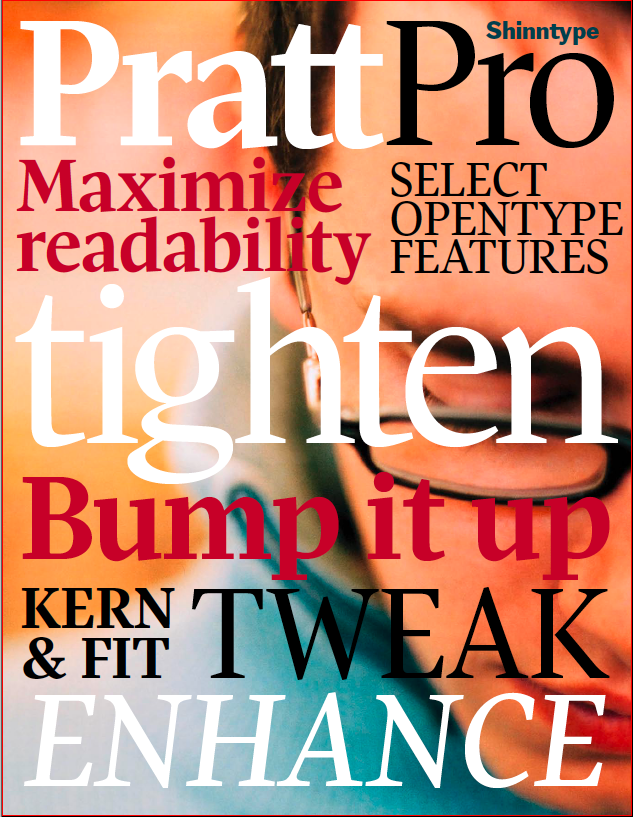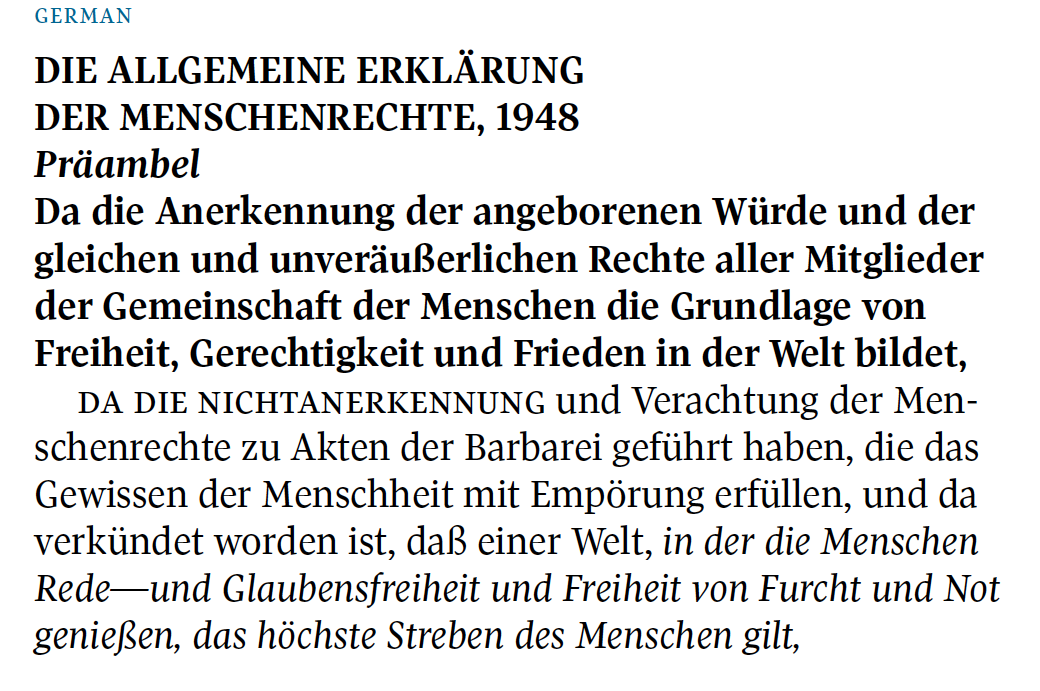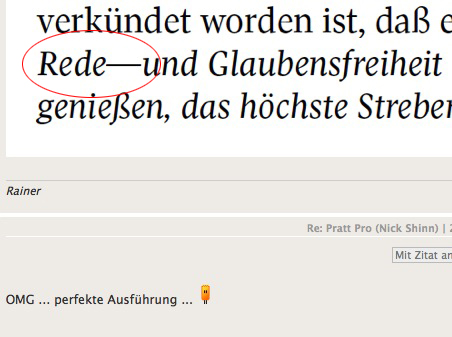
Pratt Pro (Nick Shinn)
Seit gestern ist Nick Shinns Pratt Pro der allgemeinen Öffentlichkeit zugänglich. Entwickelt für den Einsatz im kanadischen »Globe and Mail« ist sie seit 19. 1. 2009 auch als Kauf-Pro-Version erhältlich.
»With large x-height, semi-condensed proportions and short descenders, Pratt Pro is a hard-working old-style face that maintains readability in the most demanding of layouts. Despite its heft it is not without grace, displaying an economy of form, and enlivened by angled-slab detailing, thinning of ‘protected’ ?ne strokes, and a novel alternate lower case look.
When space is at a premium, Pratt Pro maximizes readability. Pica for pica, ?t the same amount of text into the same space, and Pratt Pro looks bigger than almost any other serifed text face – old style or modern – without awkward extender collisions in tight leading situations.This is clearly important for text sizes, but plays a role in multi-line headlines and decks too, where precise horizontal spacing and tight ?t call for a similar aesthetic in the vertical dimension.By the same token, when speci?ed in a layout with normal leading, a spacious effect is generated, and small size may be comfortably used for text without compromising legibility.Named after David Pratt, Design Director of The Globe and Mail, Canada’s national newspaper, who commis-sioned the face; it has been used for the paper’s body text since May 2007, setting hundreds of millions of words.
A precise, contemporary, economical face that maintains readability in the most demanding layouts.
Commissioned in 2007 for David Pratt’s radical redesign of Canada’s national newspaper, The Globe and Mail, it is available in text and headline styles, with a variety of OpenType features.«
atmet ein bisschen Weiß-Antiqua. Sehr schön!
OMG ... perfekte Ausführung ... :o
Ironie?
Das wage ich mal zu bezweifeln, dass es im Englischen üblich sei fremdsprachliche Texte falsch zu setzen :oops:
Ich fand halt die räumlich Nähe zwischen dem Satzfehler und dem "OMG … perfekte Ausführung …" so schön :cheer:
ich nehme mal an dass der geviertstrich ohne vor- und nachbreite gestaltet wurde ... wenn dann kein Raum davor und danach gesetzt wird kommt sowas raus :)
(ich meinte ja eher die Schrift an sich)
schon klar ;-)
btw: da müsste aber ein Gedankenstrich nebst Leerraum hin statt eines Geviertstriches, das meinte ich eigentlich …
So als interessierten Typolaien stößt mir der recht feine Querbalken am "e" auf ... was aber wenig an der sonst wirklich feinen Anmutung ändert.
btw: da müsste aber ein Gedankenstrich nebst Leerraum hin statt eines Geviertstriches, das meinte ich eigentlich …
ahem ...
"Rede- und Glaubensfreiheit"
soll das doch wohl heissen. Folglich gehört da ein ganz normaler Bindestrich hin:
kommt davon wenn man so mal zwischendrin was postet … natürlich ist der Bindestrich gemeint :cry::shock::peng:
:roll: nanana ... nicht gleich weinen ... ist doch nur ein klitzekleiner Strich ... kaum der Rede (die ja ohnehin frei ist) wert :)
atmet ein bisschen Weiß-Antiqua. Sehr schön!
Findest du?
Mich erinnert sie eher an eine Swift mit etwas antiquiertem Touch.
Insgesamt mag ich solche "superpraktischen" Schriften mit ausgeprägter x-Höhe, schmalen Proportionen und kurzen Unter- und Oberlängen sowieso nicht. Wobei hier noch Schwächen und Inkonsistenzen in Einzelformen hinzukommen.
Typisch shinntype, irgendwie.
Bei Typophile ist sie grad featured font, da kann man sich die Sache auch noch ein bisschen auf sich wirken lassen.
Ich find sie auf den ersten Blick solid und sicher sehr usable; aber ein bisschen gehts mir auch so wie Foniq, sowas ist nicht so mein Ding und irgendwie gehen die Ansprüche für mich auch nicht ganz auf. Aber Platzökonomie und Lesbarkeit auf einmal optimieren zu wollen ist vermutlich auch eine Art Quadratur des Kreises …
Übrigens: Bin ich doof, oder findet man die über shinntype.com wirklich (noch) nicht?
Ist bestimmt recht komfortabel zu lesen, einfach damit zu arbeiten und gut gestaltet, aber mein Geschmack ist das nicht.
na dann, wenn Kritik erlaubt ist: a, k und e gefallen nicht, Kerning unruhig. Insgesamt wackelig, da gibt's schon bessere in dieser Art: also überflüssig.
:zzzz:
Erinnert mich vom Stil her ein wenig an die fette Trump.
jene? :mrgreen:
Erinnert mich vom Stil her ein wenig an die fette Trump.
jene?
Mein lieber, lieber Bertel,
ich muss Sie leider schon wieder korrigieren und möchte so allmählich, freilich ohne Ihnen zu nahe treten zu wollen, anregen Ihr Sehvermögen gelegentlich einmal überprüfen zu lassen, denn jene von Ihnen zur Ansicht gebrachte Trump als fett zu bezeichnen ist, auch wenn sie über durchaus üppige weibliche Formen verfügt, doch ganz und gar verfehlt. Fett könnte man allenfalls, auch wenn das freilich ebenfalls nicht sonderlich charmant ist und man entschuldigend lediglich geltend machen könnte, dass wir Typografen nun einmal gewohnt sind genau und schonungslos hinzusehen, jene bezeichnen:
Findest du? Also, wenn die Dame nicht gerade den Bauch einzieht, würde ich sagen, dass regular genau das richtige Wort wäre. Nur weil heutzutage sehr viel mit condensed gearbeitet wird, heißt das nicht, dass man aus regular semi-bold machen müsste.